Utilizzare un carattere eccezionale per il tuo sito Web è molto importante in termini di design, coinvolgimento degli utenti e anche conversioni. Un buon carattere consente agli utenti di trascorrere più tempo sul tuo sito e quindi aumenta le possibilità che si convertano e acquistino la tua offerta. Potresti rimanere sopraffatto guardando il numero di caratteri disponibili online.
Con queste risorse combinate con la mia esperienza di progettazione, ho preparato un elenco dei caratteri più popolari ma migliori per l'utilizzo sul web. Google Fonts è il repository di caratteri più popolare per l'utilizzo sul Web. Ci sono oltre 915 caratteri su Google Fonts al momento della stesura di questo post. Secondo Google Fonts Analytics, di seguito sono riportati i 10 caratteri più popolari.
- Roboto
- Open Sans
- Lato
- Oswald
- Slabo 27px/13px
- Source Sans Pro
- Montserrat
- Raleway
- PT Sans
- Lora
Non si può concludere che i caratteri sopra indicati siano i migliori. Perché hai molte altre opzioni come Typekit e anche altri caratteri sicuri per il web. Tuttavia, se stai cercando i caratteri Google, utilizza uno qualsiasi dei seguenti
È sempre bene utilizzare caratteri popolari e familiari al tuo pubblico. Perché le persone si fidano di ciò che è loro familiare; dal punto di vista evolutivo. Ecco i 21 migliori caratteri che abbiamo selezionato in base alla nostra vasta ricerca sulla tipografia:
1. Roboto
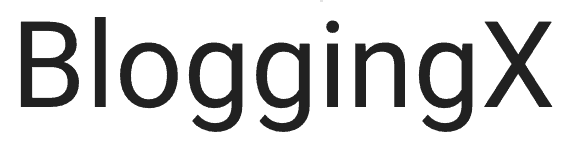
Il carattere Roboto è stato introdotto per la prima volta nel 2011 ed è stato progettato da Christian Robertson. Viene fornito con 12 stili. Roboto è una famiglia san serif e si abbina bene a Montserrat. È stato rilasciato per la prima volta nel 2011 per Android 4.0, è il carattere predefinito utilizzato nei servizi Android e Google, comprese le ricerche di Google. Troverai questo carattere su YouTube, ASUS e Vice. Roboto è ampiamente utilizzato in Photoshop, Illustrator e Sketch e la sua versione ridotta "Roboto Condensed" è utilizzata nella maggior parte dei dispositivi indossabili Android. Altre famiglie Roboto sono Roboto Slab e Roboto Mono.
2. Open Sans
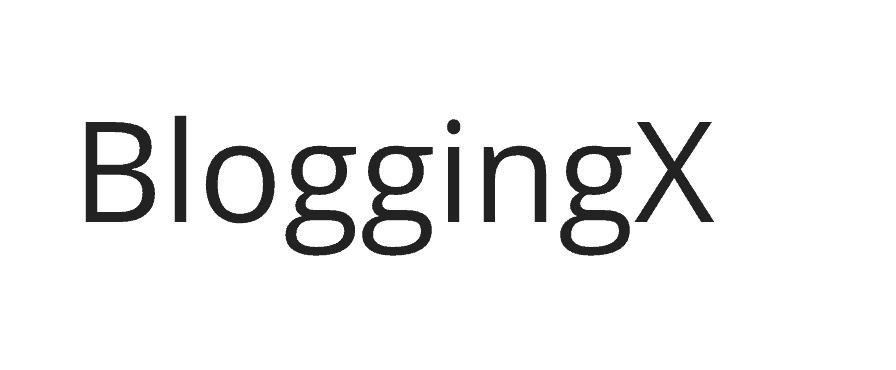
È un carattere tipografico san serif disegnato da Steve Matteson. È simile a Nunito Sans, Source Sans e si abbina bene a Montserrat, Alegreya e PT Sans. Ha un'eccellente leggibilità ed è ampiamente utilizzato per la stampa e gli annunci web di Google. Creativebloq, un noto blog di arte e design, utilizza questo carattere. Viene fornito con un'ampia libreria di caratteri che rende le sue lettere incredibilmente forti. Un'altra particolarità di questo carattere è che si sposa bene con lo sfondo nero come la pece. Molti dei blog incentrati sul design con sfondo nero vanno con Open Sans.
3. Georgia
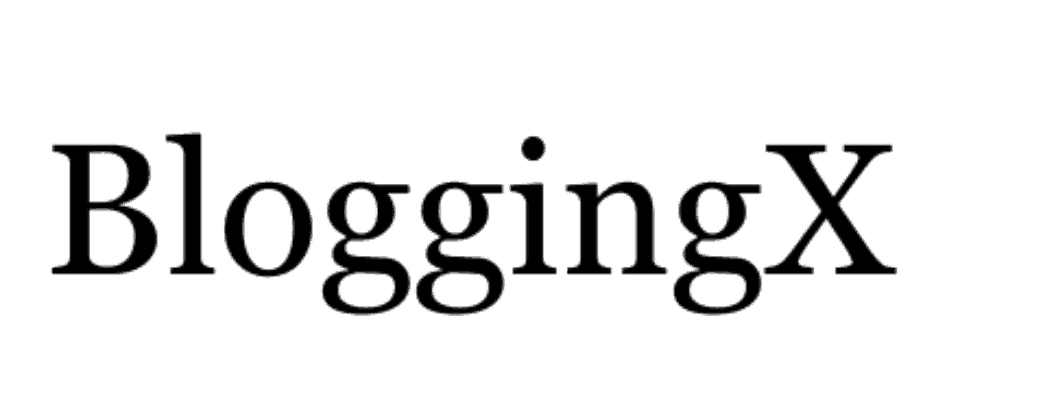
Georgia è un carattere serif suggerito da Tom Rickner e progettato da Matthew Carter con l'intenzione di utilizzarlo con schermi a bassa risoluzione dove ogni pixel è importante. Questo carattere è molto simile a Baskerville e si abbina bene con Proxima Nova, Helvetica Neue, Brandon Grotesque e Arial. La più grande piattaforma di domande e risposte al mondo, Quora, e la rete americana di trasmissione e streaming CBS utilizzano la Georgia. Inoltre, il New York Times e l'Huff Post, che sono i due grandi blog di notizie americani, utilizzano la Georgia. Georgia è un carattere compatibile con lo schermo preinstallato su computer Windows e MAC ed è utile per la stampa.
4. Merriweather
Rientra nel carattere tipografico Sans serif progettato da Eben Sorkin. Viene fornito totalmente con 8 stili diversi. Merriweather è simile a FF Tisa e Chapparal e si abbina bene a Montserrat e Merriweather sans. Una cosa grandiosa di questo carattere è che è altamente leggibile anche a piccole dimensioni e fornisce una fantastica sensazione geometrica. BoredPanda, una comunità online di arte e design creativo, Coursera, una piattaforma di corsi e Harvard.edu, un'università educativa, utilizzano Merriweather.
5. Lato
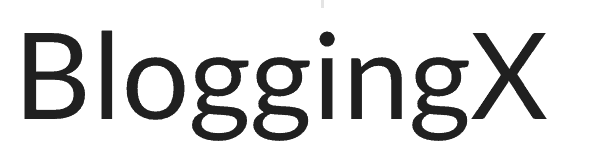
Lato rientra nella categoria san serif con un totale di 10 stili diversi. È stato progettato da Lukasz Dziedzic ed è simile a Freight Sans, Today Sans. Si accoppia con Merriweather, Firra Sans, Cardo e Yellowtail. In precedenza utilizzavo Lato sul mio blog e mi sono stufato di questo carattere e l'ho cambiato in Open Sans. Siti come Goodreads e Convince and Convert utilizzano il carattere Lato sul proprio sito web.
6. Helvetica
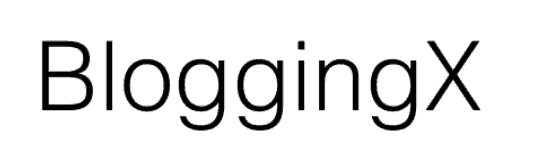
Questo carattere san serif è stato progettato nel 1957 dal designer svizzero di caratteri Max Meidinger. Facebook, Pinterest, Tumblr, Apple e Mashable utilizzano Helvetica nei loro blog. Helvetica è un carattere molto rigido e coerente e le sue forme delle lettere non sono facilmente distinguibili rispetto ad altri caratteri tipografici. Helvetica è anche popolare come Neue Haas Grotesk. Presenta una spaziatura ridotta tra i caratteri e una maggiore altezza x che rende questo carattere più facile da leggere sotto forma di testo lungo.
7. Proxima Nova
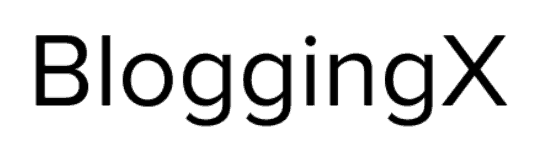
Proxima Nova è un carattere san serif disegnato da Mark Simonson. Gotham e Montserrat sono simili a Proxima Nova. A causa del loro aspetto geometrico simile, molti utenti di Gotham sono passati a Proxima Nova. Si abbina bene con Skolar. Sebbene sia un carattere tipografico costoso, offre una leggibilità straordinaria. In minuscolo ha un aspetto amichevole. Questo è diventato il carattere tipografico principale di molte grandi piattaforme di marketing online come Buzzfeed, CNET, IGN e Psychology Today.
8. Caslon Pro
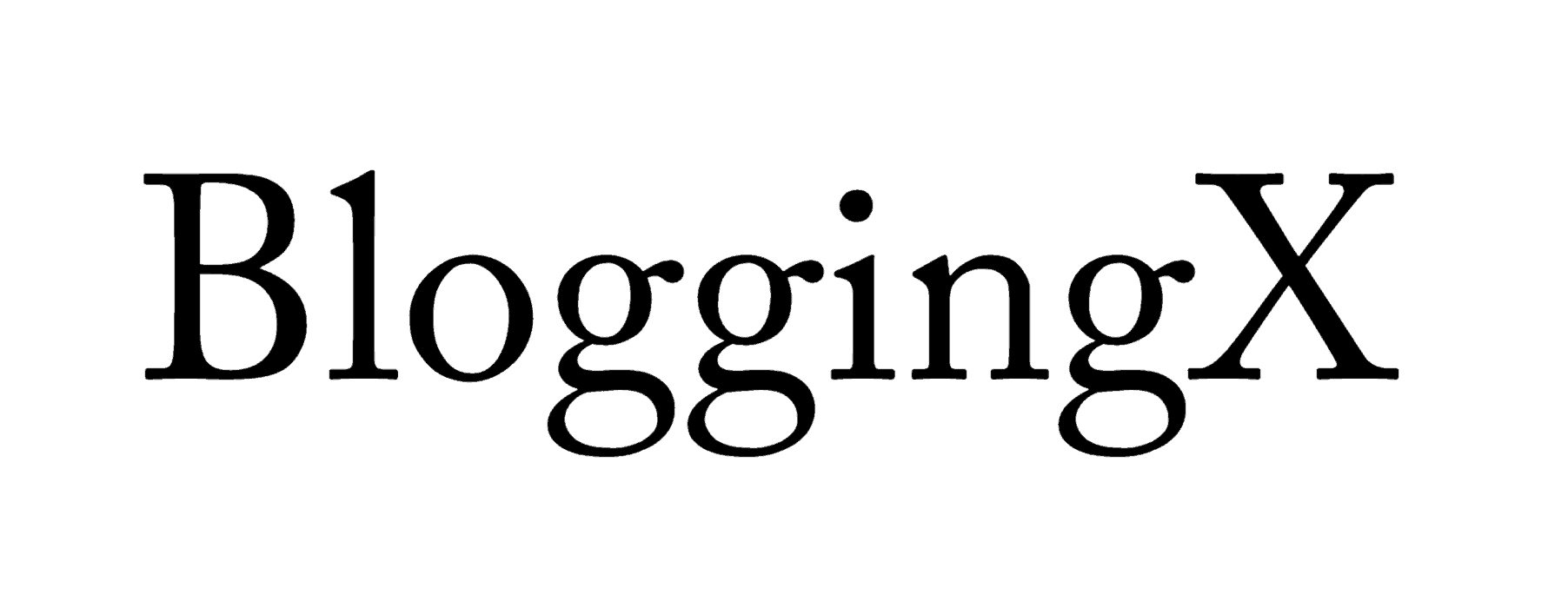
Questo carattere serif fluido e di facile lettura è stato progettato da William Caslon. Ha un buon abbinamento con P22 Underground ed è simile a Baskerville ed Ehrhardt. Il New Yorker utilizza Caslon per il corpo del testo ed è uno dei due caratteri tipografici ufficiali dell'Università della Virginia. Questo carattere dall'aspetto elegante è ampiamente utilizzato nel mondo accademico per libri di testo, giornali, riviste, enciclopedie e articoli. È un buon carattere per il corpo del testo.
9. FF Tisa
Tisa, un carattere serif disegnato da Mitja Miklavcic. Questa è la migliore alternativa per coloro che odiano Arial e Helvetica. Tisa viene fornita con 14 pesi che vanno dal sottile al nero compreso il corsivo. Le aree principali in cui Tisa è ampiamente utilizzato sono: pubblicità, packaging, editing di libri, editoria, branding di loghi, poster e cartelloni pubblicitari e anche in altri campi creativi. Tisa è un ricco carattere tipografico che fornisce supporto avanzato per funzionalità quali legature, maiuscoletto, caratteri alternativi, forme con distinzione tra maiuscole e minuscole, frazioni e caratteri in apice e pedice.
10. Garamond
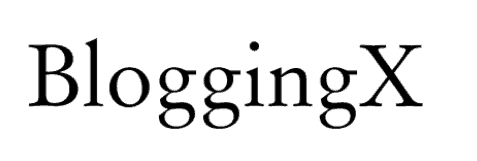
Garamond è un gruppo di molti dei vecchi caratteri serif disegnati da Claude Garamond. È un carattere molto popolare, elegante e facile da leggere. Pertanto viene utilizzato in molte applicazioni, esclusa la copia web poiché sembra un po' complessa. Fa un buon abbinamento con Oswald ed è molto simile a Sabon e Minion. È utilizzato nei libri del Dr. Seuss e nella serie di Harry Potter.
11. Slabo 27px/13px
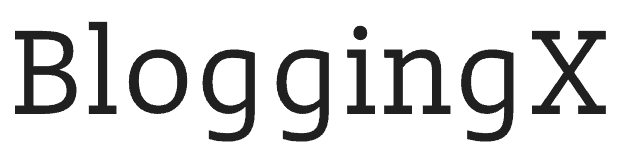
Questo carattere serif è stato progettato da John Hudson di Tiro Typeworks. Viene fornito con una scelta molto soggettiva di 2 stili. La particolarità di questo carattere è che può essere utilizzato in qualsiasi dimensione desiderata. Se vuoi che il tuo testo sia molto chiaro, puoi scegliere questo carattere poiché è leggermente condensato e fornisce titoli di facile lettura. Slabo 27px sembra superbo se abbinato a Oswald.
12. Source Sans Pro
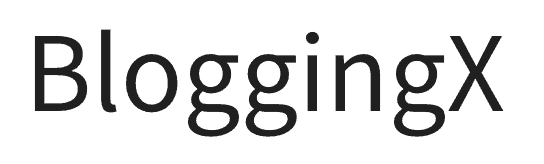
Questo carattere San Serif è stato progettato da Paul D. Hunt per Adobe ed è stato il primo carattere open source di Adobe. Viene fornito con 12 stili diversi e si abbina bene con Playfair Display. Fa parte dell'editor di codice basato su WebKit, Brackets. Supporta 6 grammature diverse: light, book, normal, semi-bold, bold e ultra-bold. Ognuno di questi viene fornito con normale e corsivo.
13. Verdana
Verdana è uno stile di carattere San Serif progettato da Matthew Carter e supporta 4 stili diversi. Ha un buon abbinamento con la Georgia ed è simile a PT SansGesta. È stato rilasciato nel 1996 e Microsoft ha incluso questo carattere per il suo sistema operativo Windows ed è stato utilizzato anche su MAC. Nella prima metà degli anni 2000 aveva acquisito estrema popolarità sul Web come carattere di sistema predefinito. Ora Facebook usa questo carattere. Uno svantaggio di questo carattere è che aggiunge spazi aggiuntivi tra le lettere e quindi non è consigliabile utilizzarlo nella stampa poiché potrebbe rallentare la leggibilità degli utenti.
14. PT Sans
PT sans è un carattere tipografico San serif più stretto e piccolo con altezza x progettato da Alexandra Korolkova, Olga Umpeleva e Vladimir Yefimov. PT Sans supporta 8 stili inclusi 2 stili stretti: normale e grassetto per i documenti e 2 stili di didascalia: normale e grassetto per il testo. Insieme a PT Sans, abbiamo PT serif e PT mono. PT Serif offre 32 stili e questi caratteri ci forniscono disegni regolari, corsivo, grassetto e corsivo grassetto. PT Sans è più adatto all'uso nei titoli ed è popolare come carattere universale e facile da usare.
15. Pluto Sans
Hannes von Dohren ha progettato questo carattere San Serif basato sull'architettura Plutone. È un carattere un po' complesso che presenta una tipografia professionale. Questo carattere di tipo aperto ha un set di caratteri esteso per supportare le lingue dell'Europa orientale, centrale e occidentale. È simile a Hurme Geometric Sans e Intro, si abbina bene con FF Tisa. È un ottimo font da utilizzare per loghi, riviste, video, confezioni di prodotti, intestazioni di siti Web, design di abbigliamento e molto altro.
16. Lora
Questo font Serif è disponibile in 4 stili diversi ed è stato progettato da Cyreal. Funziona bene sul tuo schermo e puoi usarlo anche per la stampa. Si abbina bene con Open Sans, Montserrat, Aktiv Grotesk, Circular, Santis, Lato, Proxima Nova, Gotham Rounded, Noto Serif e Texta. PopSugar, una piattaforma mediatica e tecnologica americana, utilizza questo carattere. È ben ottimizzato per gli schermi e funziona bene nella stampa. La sua tipografia e l'aspetto memorabile con curve spazzolate lo rendono adatto all'uso per narrazioni e saggi.
17. Noto Sans
Questo carattere tipografico San Serif è dotato di 14 stili ed è un buon abbinamento se utilizzato con Lora. Noto è una delle migliori famiglie di caratteri open source per tutte le lingue del mondo e rende il Web straordinario con il suo supporto per tutte le lingue. Si abbina bene con Lato, Gilroy, Museo Slab, Montserrat, Noto Serif, Roboto e DIN. Reddit utilizza questo stile di carattere. Per ora, Noto Sans è presente in più di 1.800.000 siti web.
18. Montserrat
Questo carattere San Serif è stato progettato dalla designer argentina Julieta Ulanovsky ed è disponibile in tre varianti. Viene fornito con il maggior numero di stili, ovvero 36 stili. È un buon abbinamento se usato con Foro. Montserrat è l'alternativa gratuita più vicina a Gotham e Proxima Nova. Il set di caratteri di Montserrat è più ampio di Arial o Helvetica. Il minuscolo Montserrat sembra molto carino con la sua buona altezza x, la sua geometria è ben strutturata con grande semplicità.
19. Raleway
Raleway, un carattere tipografico San Serif è stato progettato da Matt McInerney come un unico peso. Nel 2012 Pablo Impallari e Rodrigo Fuenzalida lo hanno ampliato. Raleway è una delle grandi famiglie di caratteri e supporta 18 stili. Raleway Dots e l'approccio punteggiato sono molto vicini tra loro. Raleway costituisce un buon abbinamento se utilizzato con Roboto Slab. Raleway Dots è un'altra grande famiglia di Raleway. Ha pochissima enfasi sul testo ed è stato realizzato principalmente per i temi WordPress.
20. Work Sans
Work Sans è stato progettato dal type designer australiano Wei Huang. Questo carattere san serif open source è disponibile in 9 stili diversi. È ben ottimizzato per l'uso sugli schermi. È abbastanza simile a Karla, acero e Tenso. Funziona alla grande se abbinato a Bitter. Questo stile è stato influenzato dalle prime grottesche. Funziona bene sia per Windows che per Mac OS.
21. Monaco
Questo carattere San Serif è stato progettato da Susan Kare e Kris Holmes. È stato originariamente rilasciato da Apple per il suo sistema operativo Mac. L'attuale Python IDLE in esecuzione con Mac OS X EI Capitan utilizza Monaco come carattere predefinito. Nel 2009, quando fu introdotto Mac OS X Snow Leopard, Monaco fu sostituito da Menlo come carattere a spaziatura fissa predefinito.
5 combinazioni di caratteri popolari
Scegliere la giusta combinazione di caratteri utilizzati nei titoli e nel corpo del testo è molto importante.
Ecco alcune delle buone combinazioni di caratteri:
1. Oswald e Open Sans : questa è un'ottima combinazione che utilizzo da molto tempo. Con Oswald come intestazione, puoi utilizzare caratteri come Open Sans, Lato, Helvetica, Roboto nel corpo del testo. Questa coppia è ottima per i siti in cui è necessario aggiungere un sapore di mascolinità.
2. Montserrat e Merriweather : questa coppia funziona benissimo per i siti Web di notizie e media, in cui è necessario utilizzare caratteri serif nel corpo.
3. Nunito e Open Sans : entrambi sono in stile sans serif, quindi se vuoi rappresentare un sito web moderno incentrato sul design, senza l'uso di caratteri condensati, potresti voler utilizzare questa combinazione
4. Alegreya e Lato: Alegreya è un font serif dall'aspetto fantastico, puoi usarlo nei titoli e Lato (sans serif) nel corpo. Dà un fantastico aspetto ibrido al tuo sito web.
5. Oswald e EB Garamond: Puoi usare Oswald nei titoli perché è abbastanza condensato. Anche in questo caso l'uso di Garamond per il corpo del testo è molto soggettivo. Se per qualsiasi motivo non ti piace Garamond, caratteri come Roboto, Open Sans, Merriweather, ecc.
Puoi utilizzare strumenti come FontPair per verificare altri abbinamenti di caratteri popolari. Sentiti libero di sperimentare!